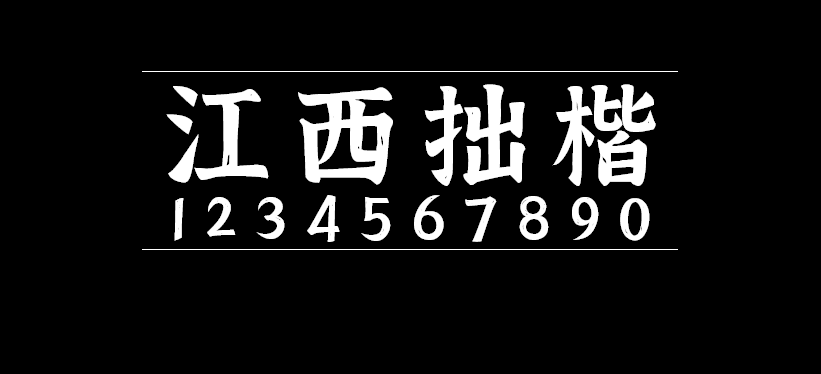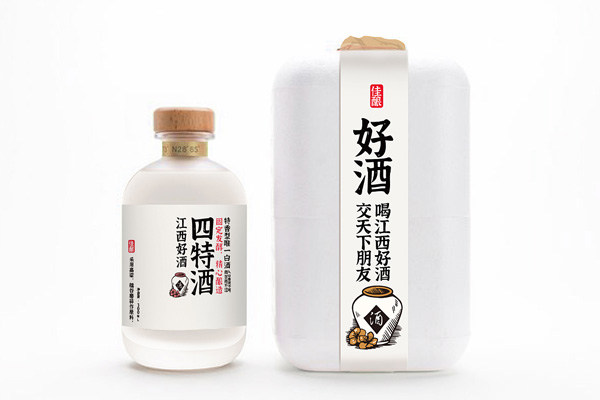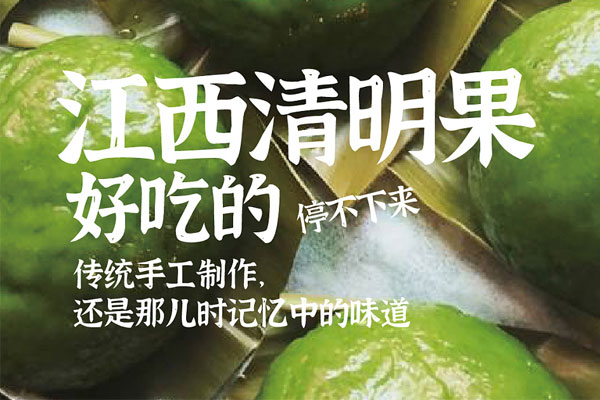
江西拙楷
江西拙楷是设计师黄煜臣的第一套字体,是一套手写楷体,相比电脑中标准化制作的楷体,这套字体的笔画会带有一些书写的痕迹,每个字的笔画是没有统一标准的,所以看上去显得不够规范,但是会有一种手写的自然之感。这套字体从写手稿开始到最终成品,花了近半年时间,仅仅是调节点,就花了20多天。 这套字体作者经过仔细考虑后决定免费提供给大家使用!可以免费在任何传播渠道使用,包括商用。如果你喜欢这款字体,也可以打赏形式支持作者,作者公众号:字体树(ID:fontree)